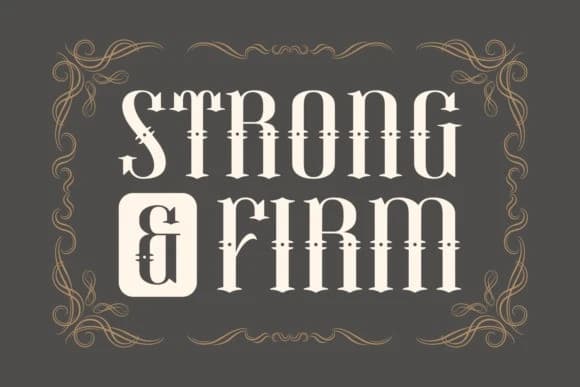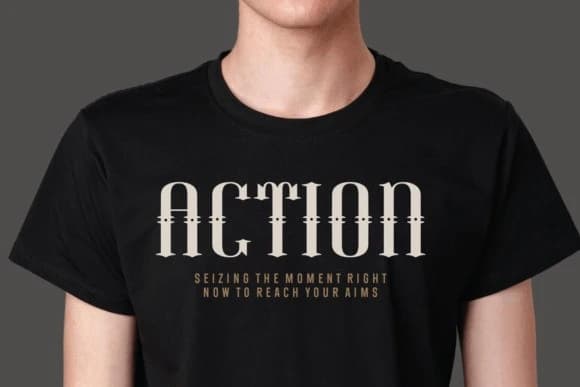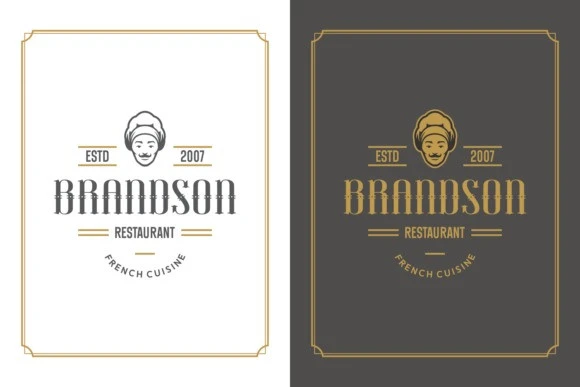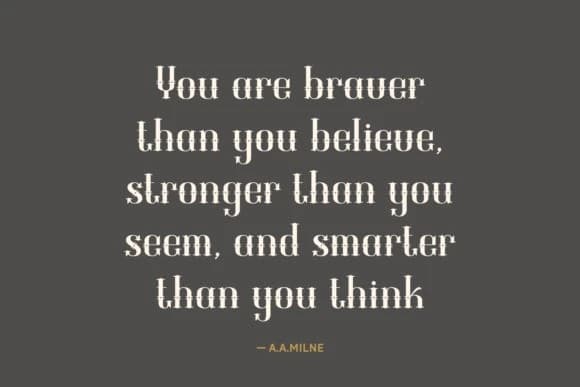
Strong and Firm Font
Strong and Firm Font, klasik Blackletter tasarımını vintage bir hava ile büyüleyici bir karışım olarak sunar. Bu kusursuz temiz, zanaatkarca tasarlanmış font son derece çok yönlüdür ve herhangi bir ortamda kusursuz bir biçimde kendini gösterir – ister web, ister parlak dergi sayfaları ya da bir tişö
Strong and Firm Font, klasik Blackletter tasarımının vintage bir çekiciliğiyle büyüleyici bir karışımı. Bu kusursuz temiz, el yapımı bir yazı tipi çok yönlüdür; ister web, parlak dergi sayfaları veya rahat bir tişörtün pamuklu kumaşı olsun, kusursuzca her ortamda kendini gösterir.